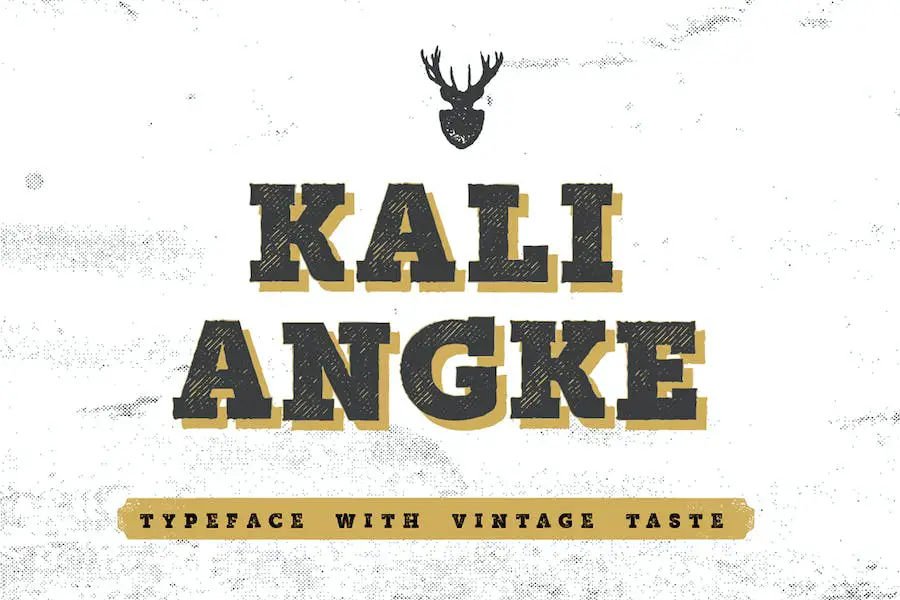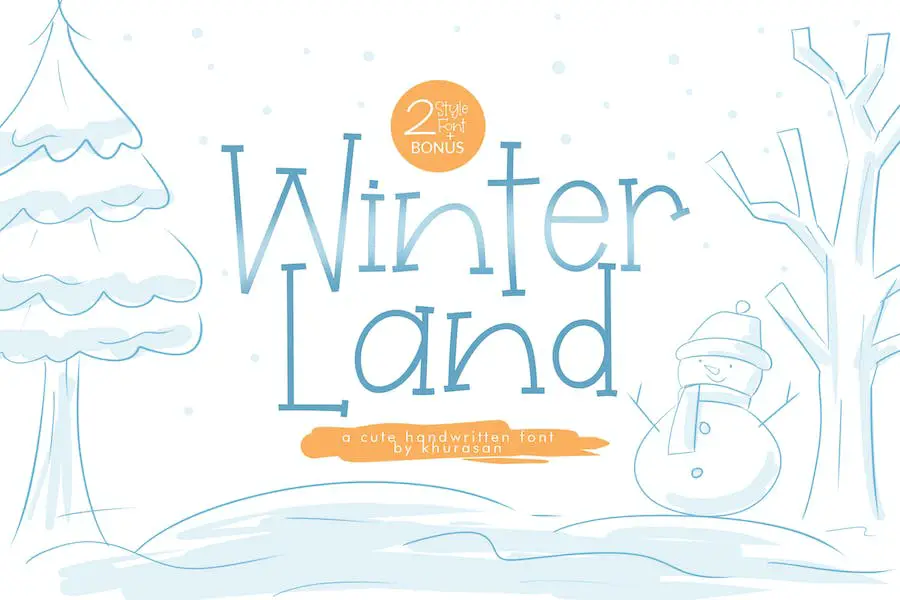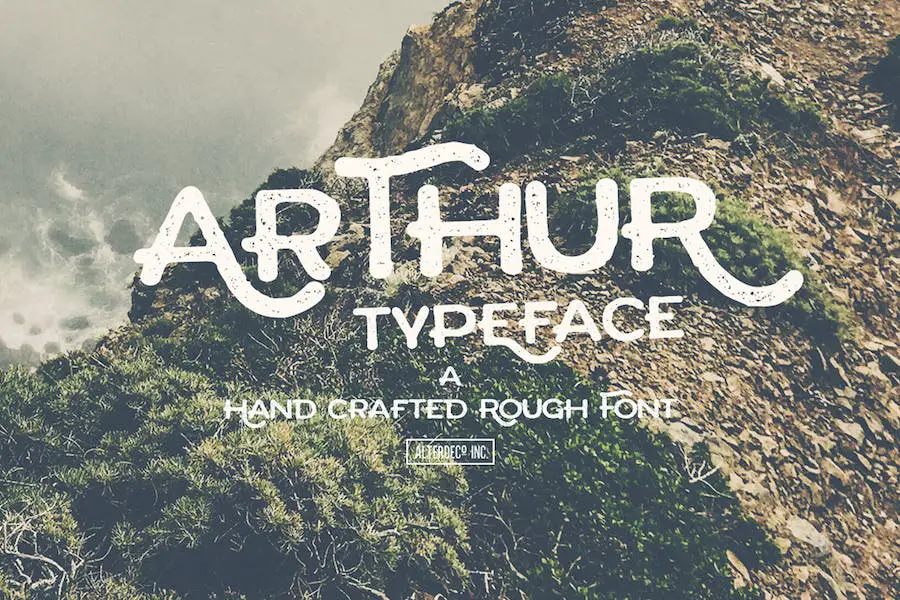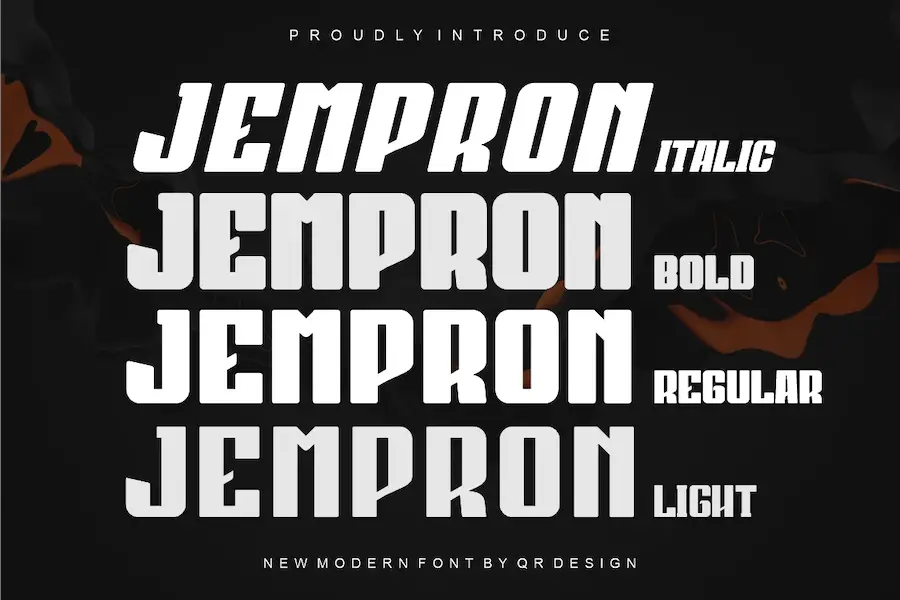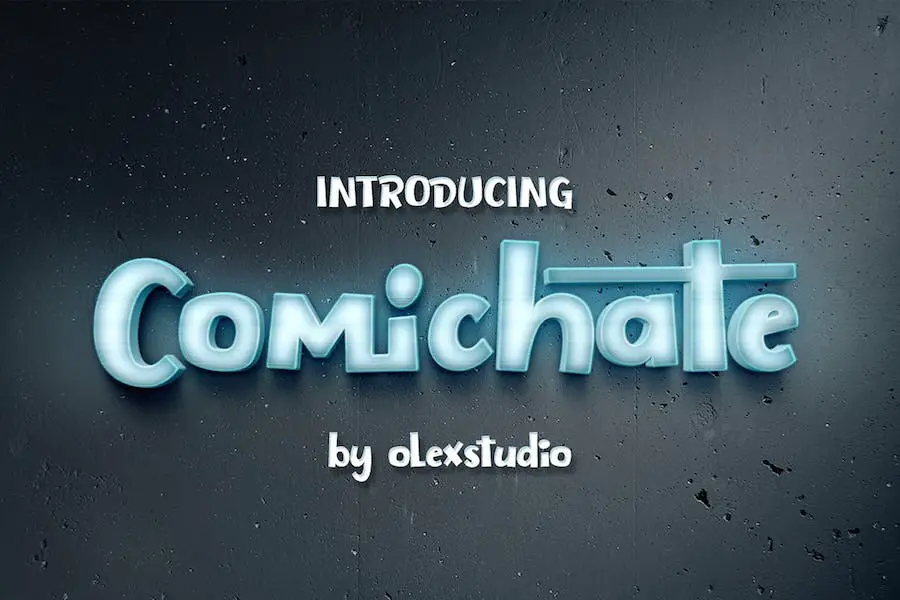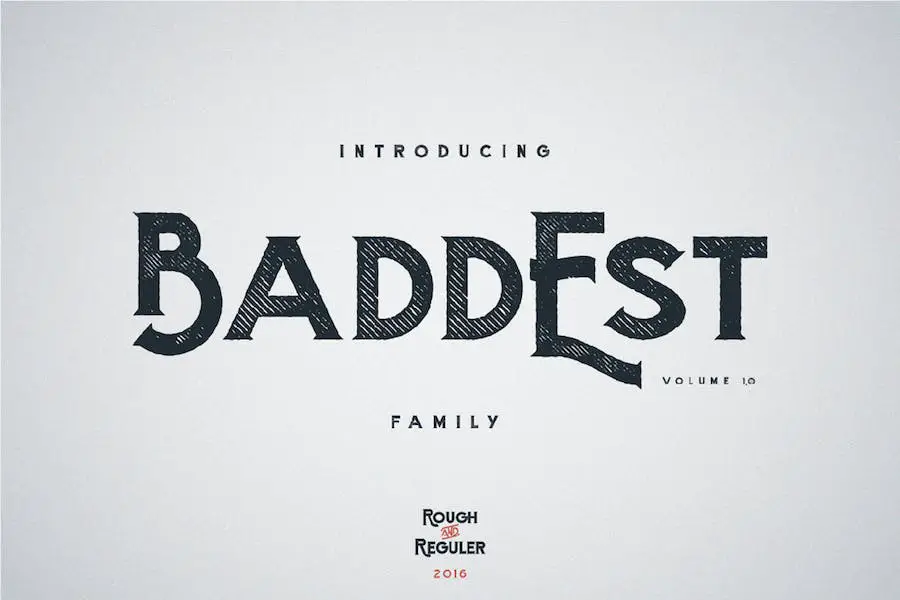
30 melhores fontes de camisetas 2023 (grátis e premium)
Publicados: 2023-08-22Você é um designer gráfico em busca da fonte perfeita para levar seus designs de camisetas para o próximo nível? Não procure mais! Nesta postagem do blog, selecionamos uma lista das 30 melhores fontes para camisetas que o ajudarão a elevar seus projetos e destacá-los da multidão.
Você deve estar se perguntando por que as fontes são tão importantes quando se trata de design de camisetas. Bem, a fonte certa pode fazer toda a diferença. Ele dá o tom, transmite uma mensagem e adiciona personalidade aos seus designs.
Com a fonte certa, você pode transformar instantaneamente uma camiseta básica em uma obra de arte. E com a grande variedade de fontes disponíveis, há algo para cada estilo e projeto.
Neste artigo, mergulharemos no mundo das fontes para camisetas e destacaremos as 30 principais fontes perfeitas para qualquer projeto. Esteja você procurando um visual ousado e ousado ou uma vibração divertida e divertida, nós temos o que você precisa.
Então, vamos começar e explorar juntos o incrível mundo das fontes para camisetas!
Melhores fontes premium para camisetas
Quer levar os designs de suas camisetas para o próximo nível? Não procure mais! Nesta seção, compilamos as melhores fontes premium para camisetas que farão seus designs se destacarem da multidão. Não perca essas fontes de primeira linha – confira-as e eleve seus projetos hoje mesmo!
Caneta esferográfica
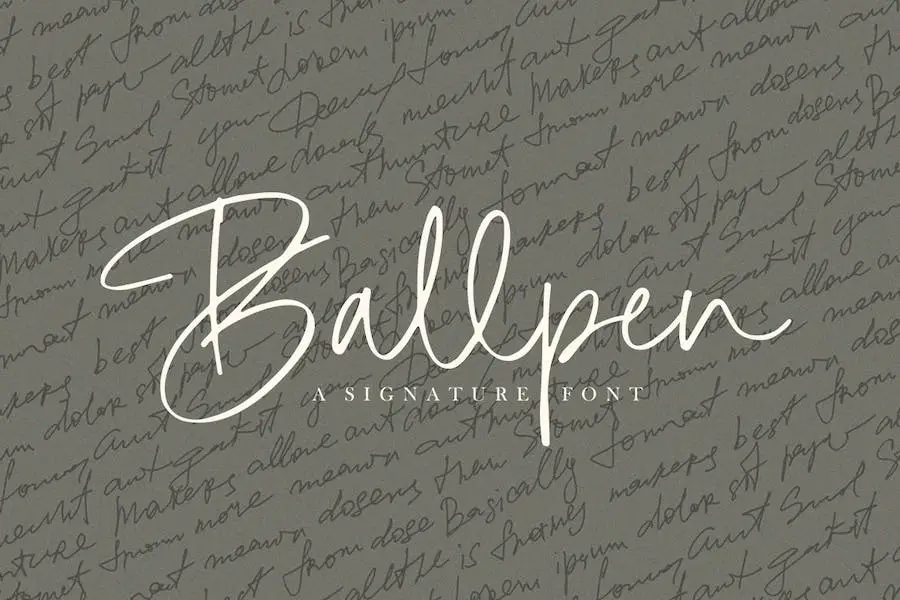
Ballpen é uma fonte elegante e exclusiva, perfeita para designers gráficos que buscam aprimorar o design de suas camisetas. Com seu visual único e estiloso, esta fonte irá adicionar um toque de sofisticação a qualquer projeto.
Esteja você projetando uma camiseta inspirada em tatuagem ou simplesmente queira elevar seu design, Ballpen é a fonte para você.
Esta fonte tem um estilo distinto e atraente que fará com que seus designs se destaquem da multidão. Seus traços elegantes e belas curvas conferem-lhe um visual clássico e atemporal que certamente impressionará.
Um dos maiores atributos da Ballpen é a sua versatilidade. Ele pode ser usado para uma ampla variedade de projetos de design, incluindo camisetas, logotipos, pôsteres e muito mais. A natureza limpa e legível desta fonte facilita a incorporação em vários estilos e temas de design.
Assistir
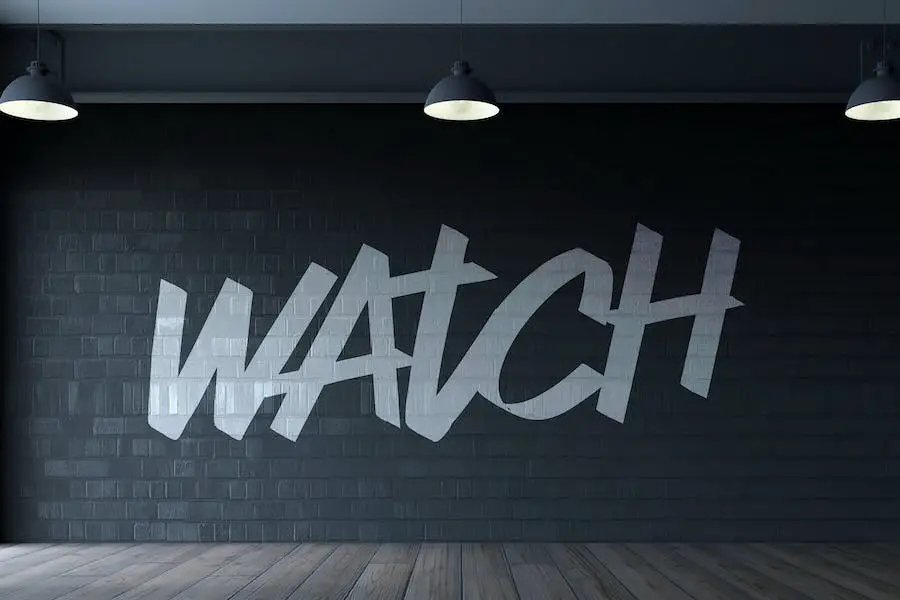
Watch é uma fonte que se inspira em fontes de marcadores e estilos de graffiti. É perfeito para criar manchetes atraentes, desenhar pôsteres, personalizar camisetas, capas de álbuns e qualquer outra coisa que exija um toque de graffiti.
Com o Watch, você pode adicionar instantaneamente uma vibração urbana e ousada aos seus projetos de design. As suas linhas arrojadas e dinâmicas captam a energia bruta da arte de rua, tornando-a uma excelente escolha para quem procura marcar presença.
Esteja você criando um design de camiseta ousado e rebelde ou projetando um pôster marcante que exige atenção, o Watch tem o que você precisa.
Esta fonte realmente incorpora o espírito do graffiti. Suas arestas ásperas e traços irregulares dão aos seus designs uma sensação autêntica e corajosa, garantindo que eles se destaquem da multidão. É a escolha perfeita para quem deseja adicionar um toque de arte urbana aos seus projetos.
Bloqueadores
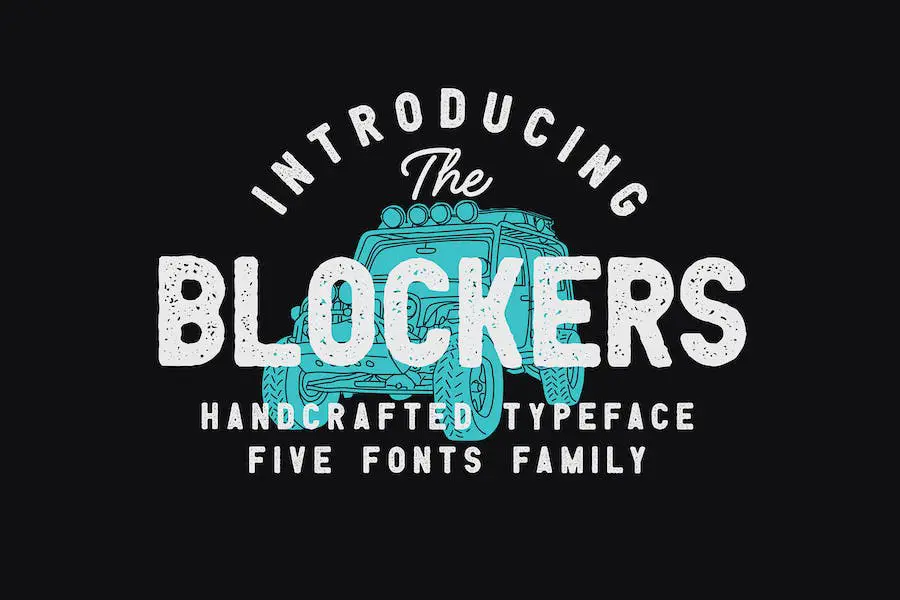
Blockers é uma fonte exclusiva, projetada especificamente para designers gráficos que buscam aprimorar seus projetos com uma fonte elegante e versátil. Esta fonte sem serifa oferece uma coleção de cinco famílias de fontes que foram habilmente elaboradas à mão.
É a escolha perfeita para criar designs atraentes de camisetas, gráficos de inspiração vintage, placas, emblemas, etiquetas e muito mais.
Os Blockers foram meticulosamente projetados para garantir que cada detalhe seja perfeito. Sua natureza cuidadosamente artesanal significa que cada letra recebeu atenção individual, resultando em uma fonte esteticamente agradável e visualmente atraente.
As famílias de fontes incluídas nos Blockers oferecem uma variedade de estilos e variações, permitindo aos designers explorar diferentes opções e criar designs exclusivos.
Um dos principais atributos dos Blockers é a sua versatilidade. Esteja você projetando um gráfico de camiseta ousado e moderno ou um logotipo nostálgico e de inspiração vintage, esta fonte tem algo para todos.
Suas linhas limpas e nítidas facilitam a leitura, enquanto seu caráter e charme conferem-lhe uma personalidade distinta que fará com que seus designs se destaquem.
Irrisório
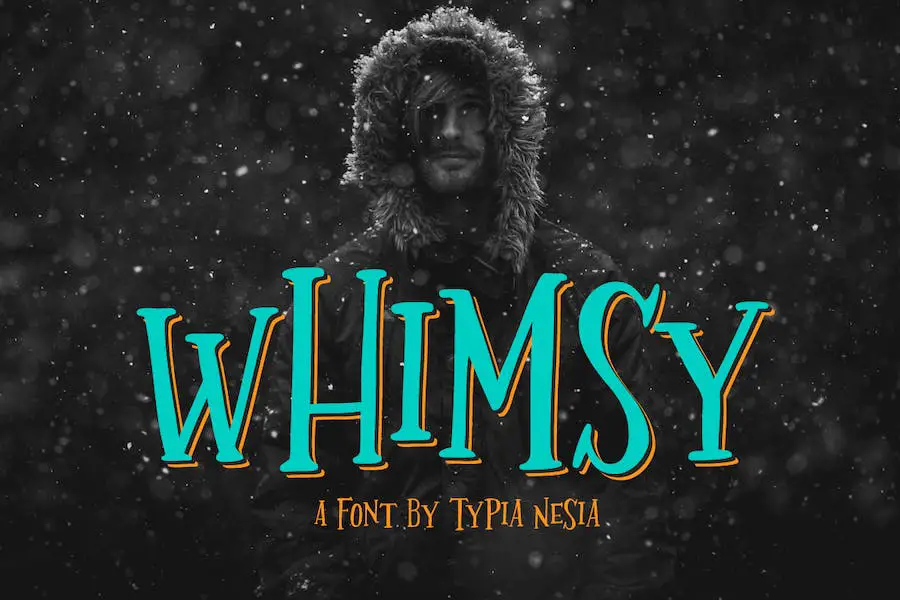
Whimsy é uma fonte exclusiva que adiciona um toque de charme extravagante a qualquer projeto de design. Como uma fonte de exibição de fantasia feita à mão, ela traz uma sensação de diversão e criatividade aos seus designs. Com seu estilo diferenciado, é perfeito para projetos que exigem um toque de magia e imaginação.
Os atributos do Whimsy o tornam uma excelente escolha para designers gráficos que buscam aprimorar seus projetos. A natureza artesanal da fonte adiciona um toque pessoal e artesanal aos seus designs, fazendo-os se destacar da multidão.